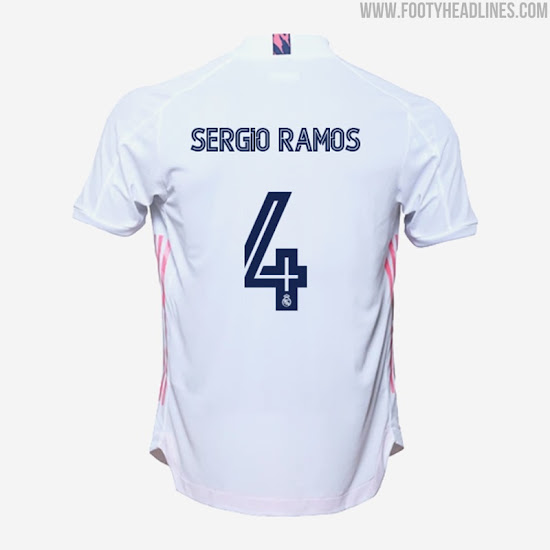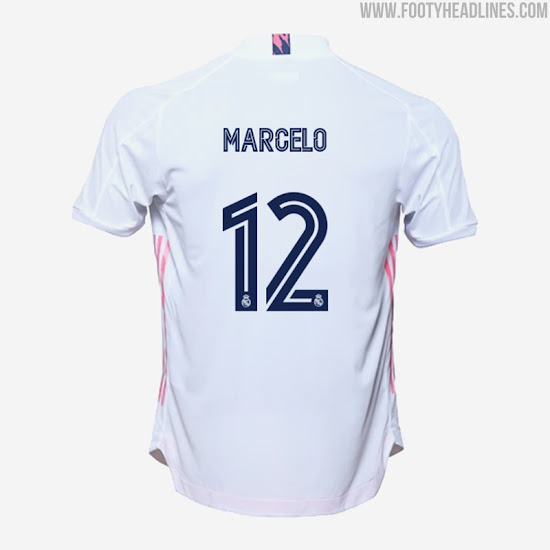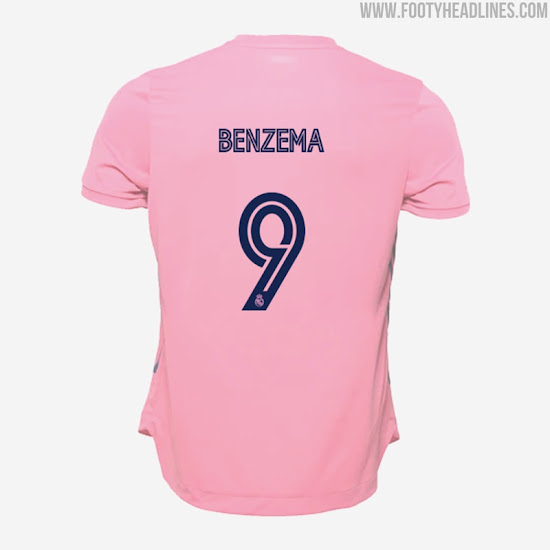
Real Madrid 20-21 Schriftart veröffentlicht
Die heutige Veröffentlichung der Real Madrid 20-21 Trikots beschert uns auch einen ersten Blick auf die offizielle neue Schriftart des Klubs, die ab der nächsten Saison verwendet werden soll. Real Madrid ist einer der wenigen Klubs, die jedes Jahr eine neue Schriftart debütieren.
Da La Liga eine einheitliche Schriftart verwendet, wird Real Madrid diesen Stil nur international, vor allem in der UEFA Champions League sowie in der Copa del Rey, verwenden. Wir werden sie zum ersten Mal auf dem Platz im Achtelfinale der Champions League gegen Manchester City erleben.
Real Madrid 20-21 Schriftart
Dieses Bild zeigt die neue Schriftart auf dem Real 2020-21 Heimtrikot von Benzema.
Die neue Schrift führt ein moderneres Aussehen ein, obwohl sie sich an den klassischen Fußballschriften der 1980er und 90er Jahre orientiert.
Die klaren Grundformen weisen geometrische Ausschnitte auf, die sowohl den Ziffern als auch den Buchstaben eine einzigartigere Note verleihen.
Die Schrift ist bei allen bisher vorgestellten Trikots - Heim-, Auswärts-, TW-Heim- und TW-Auswärtstrikot - marineblau.